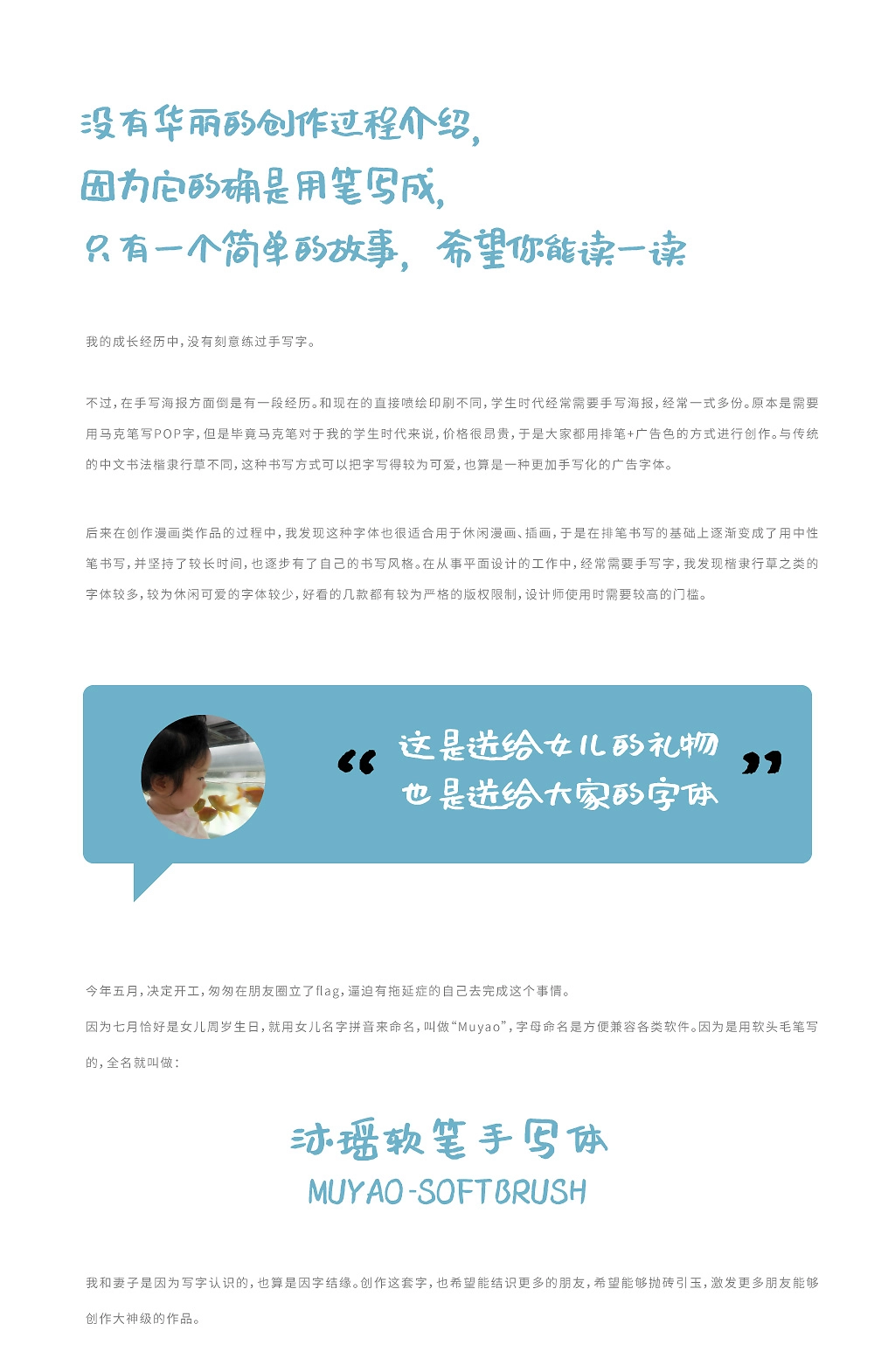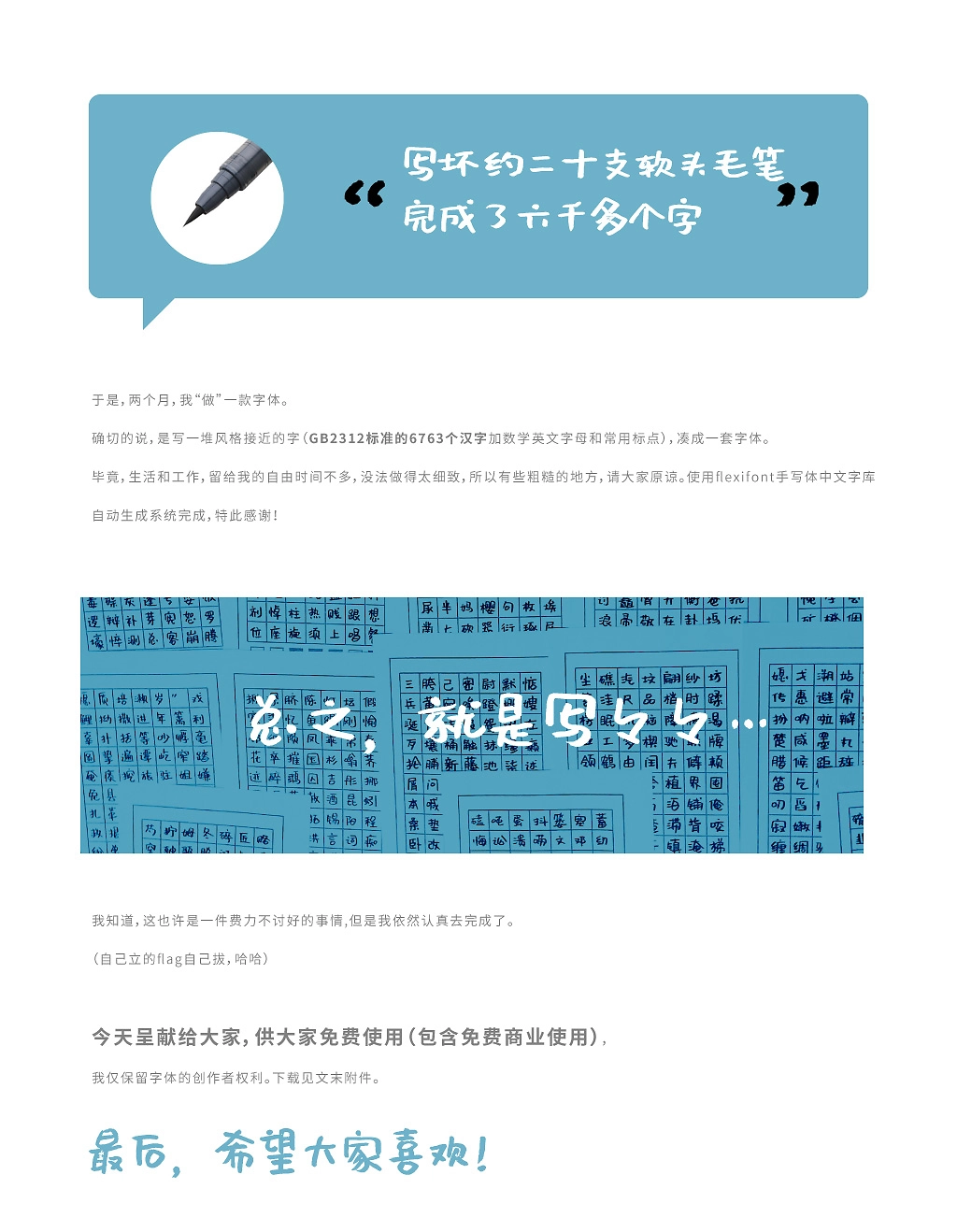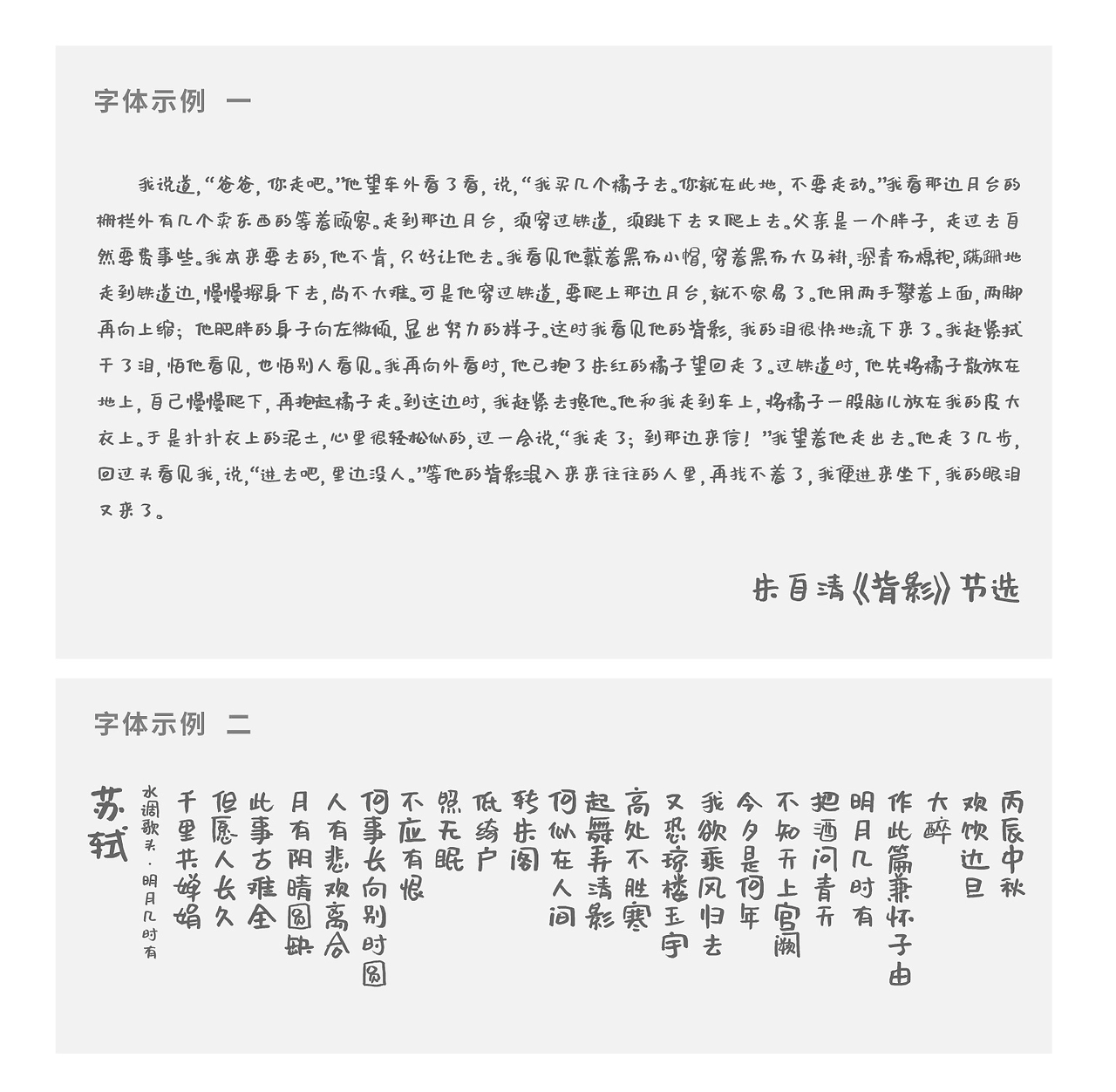
沐瑶软笔手写体
字体简介
“沐瑶软笔手写体”是一款由站酷设计师“春颜秋色”创作的免费中文字体,发布于2018年7月,以其女儿名字“Muyao”命名,寓意送给女儿的礼物。这款字体属于手写风格,采用软头毛笔书写,笔画圆润自然,线条流畅,呈现出可爱、活泼的卡通感。它包含6763个汉字(符合GB2312标准),覆盖常用简体中文字符,以及英文字母、数字和常见标点符号,总字符数约7000多个。